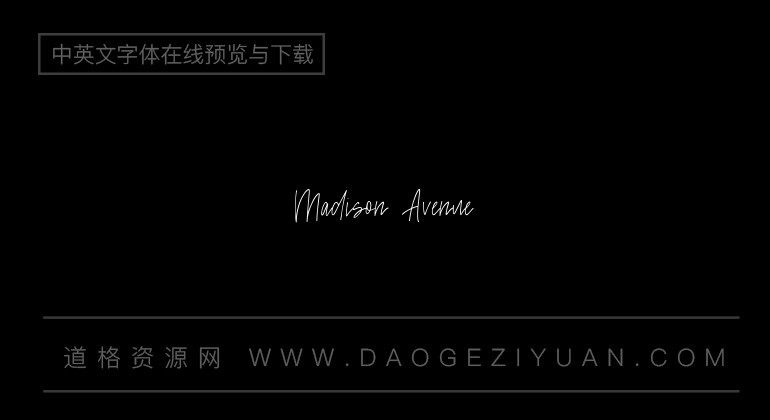
Madison Avenue
Madison Avenue是一种时尚和精致的手写字体,它的风格适用于广告和品牌设计。这种字体设计的初衷是模仿20世纪50年代和60年代广告行业的典型手写字体,因此它的命名来自于纽约市的广告中心Madison Avenue。Madison Avenue 字体的特点是流畅的笔画和圆滑的边缘,具有一定的装饰性,但不会过于华丽,仍然保持简约现代的风格。这种字体通常用于印刷品、海报、包装设计和品牌标识等领域。
Madison Avenue是一款非常不错的手写艺术字体,具有很好的视觉感,适合于文化类的宣传设计、商业类品牌的广告和产品包装设计以及个性化文字排版等较多场景。
Madison Avenue字符映射图